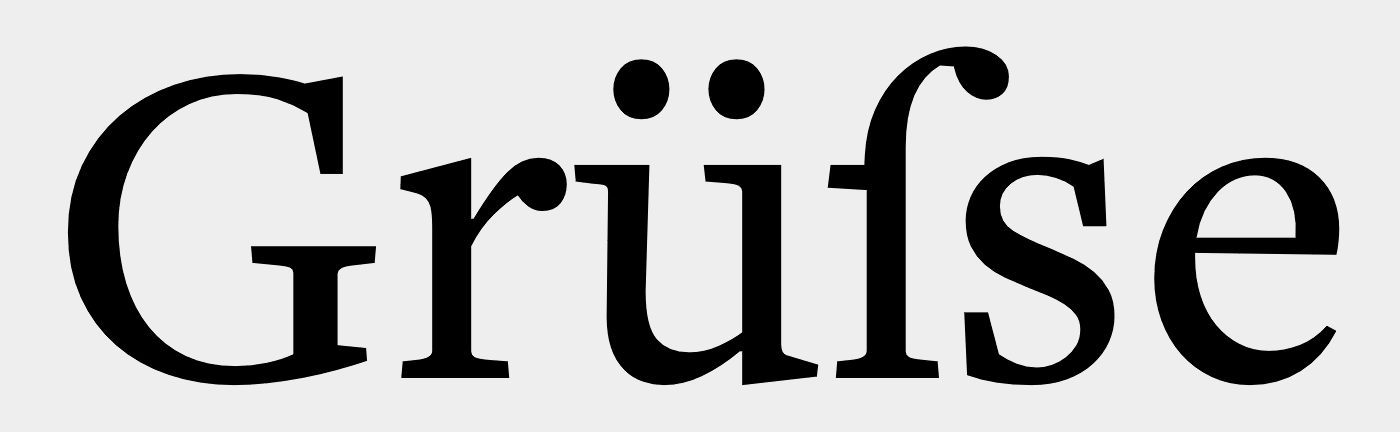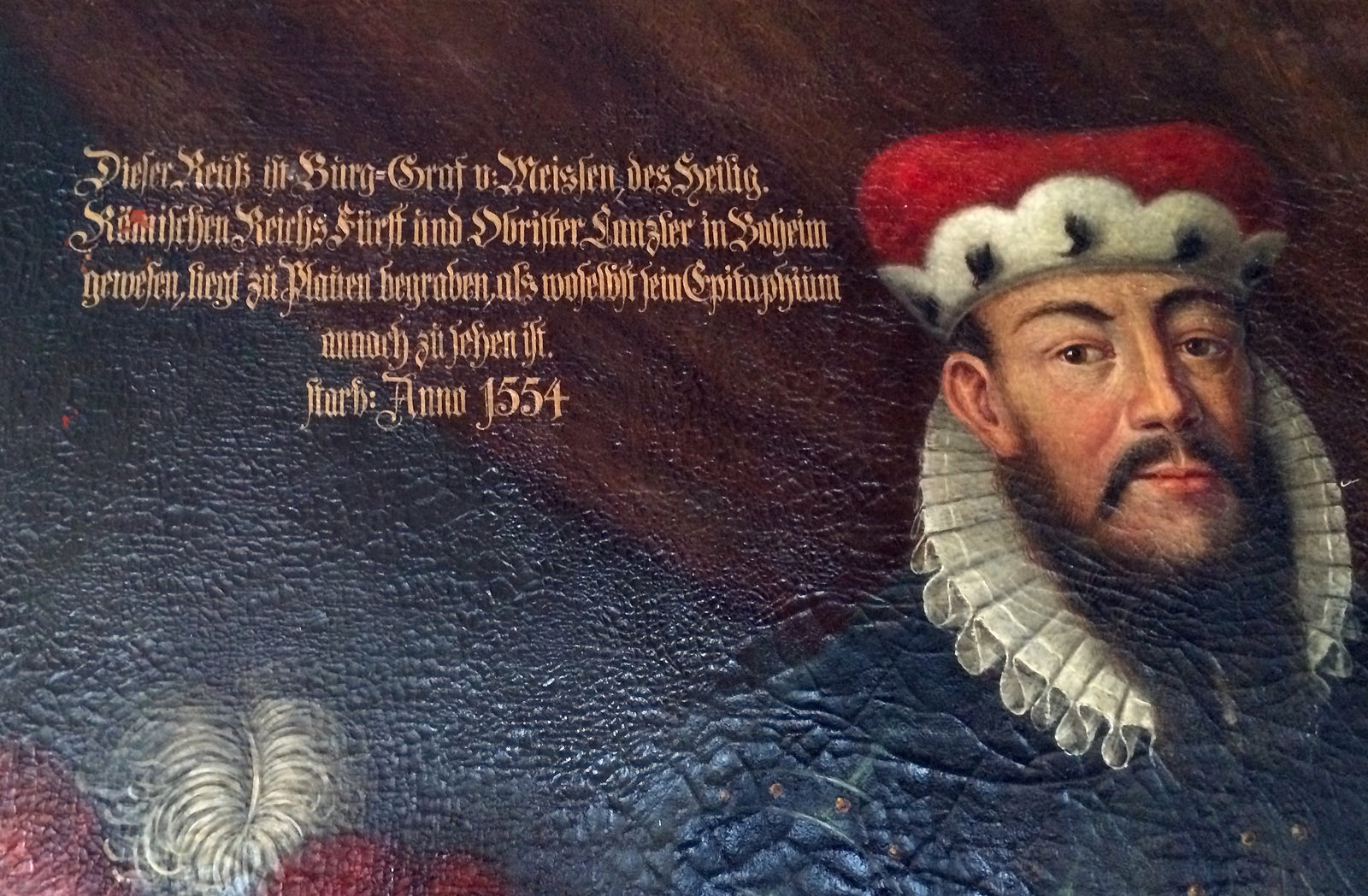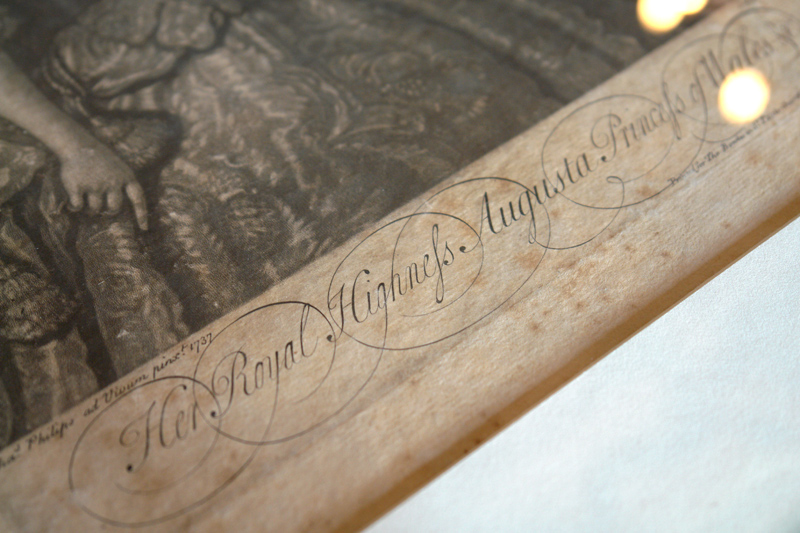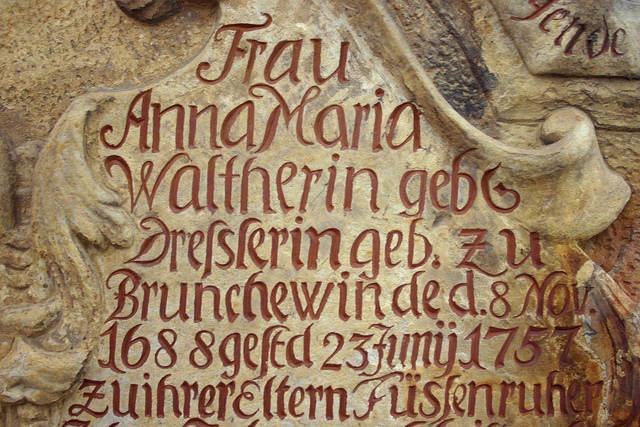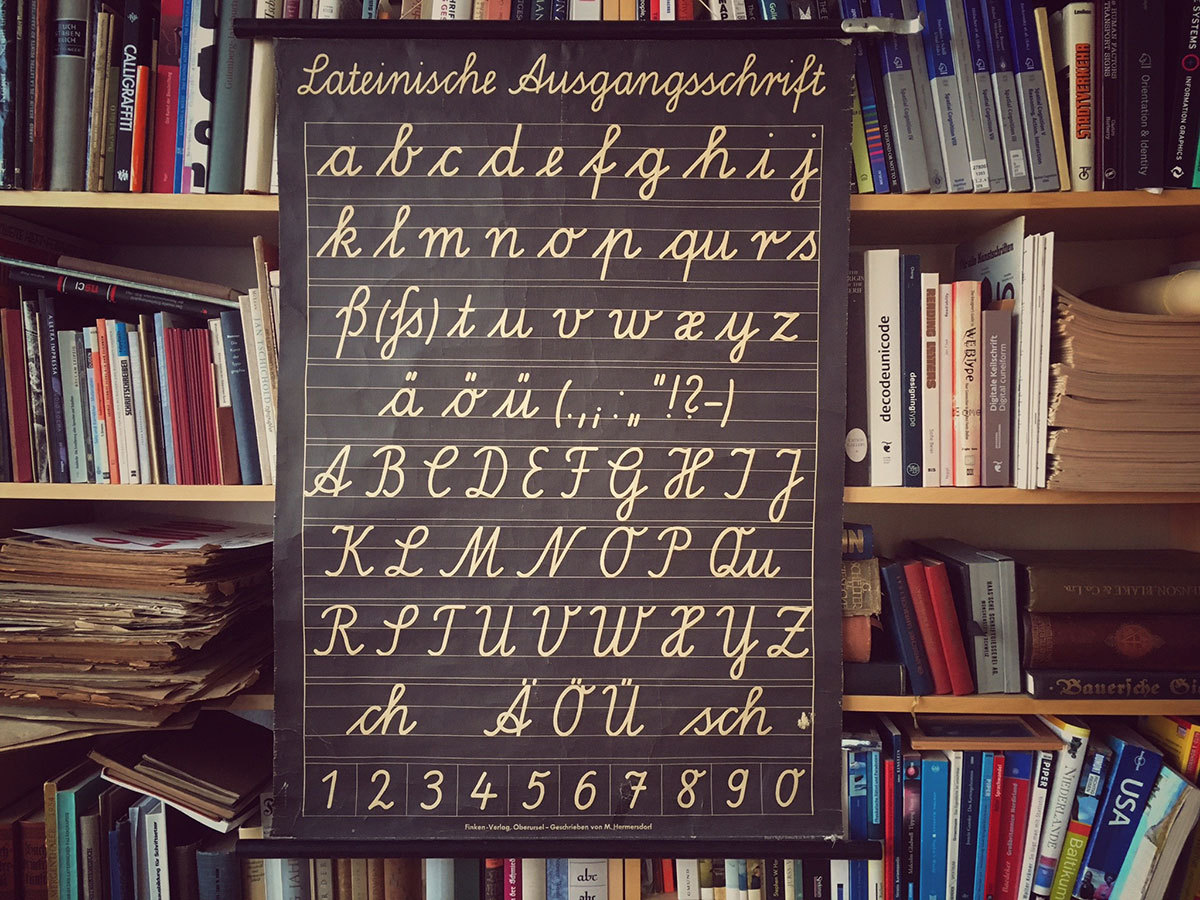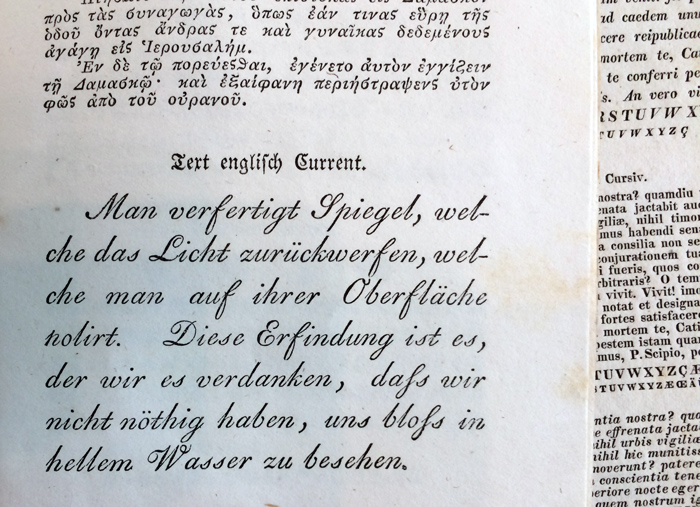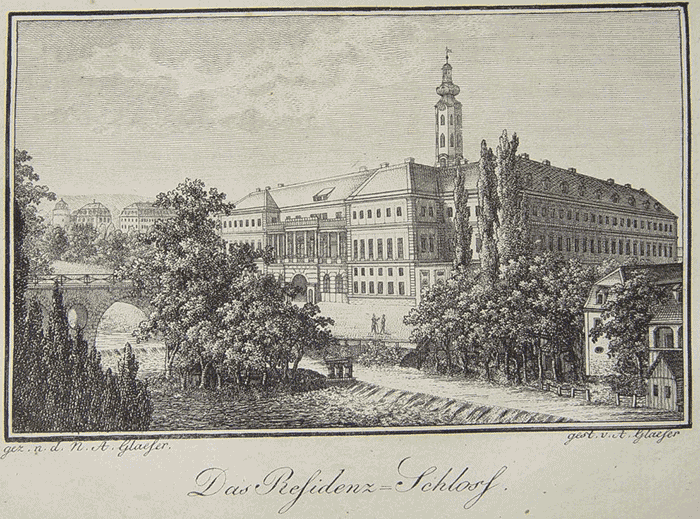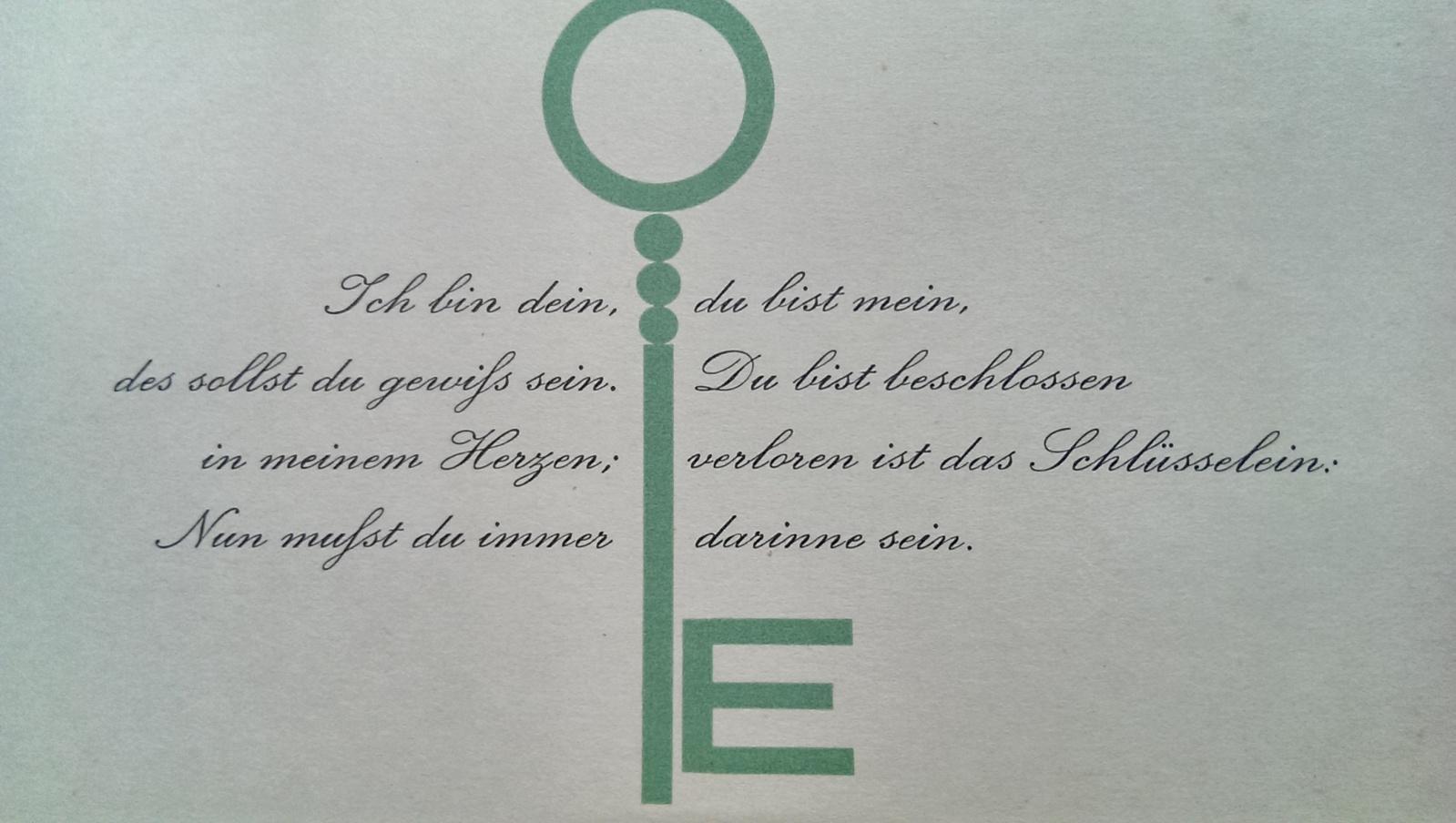
Das ist ein Latein-Schreibschift-langers-s, dieses wurde tatsächlich wie das h in Kurrentschrift geschrieben, und sorgt gerne für Verwirrung bei gemischter Schreibung in alten Dokumenten. Allerdings ist Straſse nicht so wirklich kosher.
Ich habe ja nicht behauptet, das die Glyphe ſ oder als Ligatur als ſs nicht in Ordnung wäre, nur müsste es, nutzt man das lange s (ſ) dann  eben nicht ſs sein, wenn dahinter noch ein e folgt. die ſs-Ligatur ist für die Heysesche s-Schreibung der aktuellen Rechtschreibung gedacht, wenn, wegen der Volalkürzung nicht ß verwendet wird, und man das lange ſ verwenden möchte, z.B. im Fluſsſchiff. in den von Ralf gezeigtem Beispiel steht ſs ja am Wortende.
ich finds auch hübsch, aber auch total verwirrend. will dauernd musss oder Strafse lesen.
Nun, da ich mich in letzter Zeit ziemlich in Kurrentschrift eingeleseh habe, lese ich im ersten Moment hier "muhs" und "Strahse"
Die Schreibschriftvariante ist wirklich hübsch!  :nicken:
In einigen zeitgenössischen Schriften ist diese Glyphe ebenfalls enthalten:
Aber in dieser Satzschrift-Form finde ich sie sehr irritieren, muss ich gestehen. Ich habe hier vor langer Zeit schon mal irgendwo darüber geschrieben, wie sehr mich diese ß-Form beim Lesen stört. Ich habe das komplette Buch »Wirklich gute Logos erklärt« durchgelesen, aber ich habe mich mit zunehmender Seitenzahl immer mehr über diese Buchstabenform der verwendeten serifenlosen Fließtextschrift geärgert, weil ich da immer immer immer »fs« gelesen habe. Das ist in meinen Augen reine Gestaltereitelkeit und kein Dienst am Leser. Sorry!  :-)
Ja, ich denke ebenfalls, dass die Variante für heutige Lesegewohnheiten ungeeignet ist. Ich mutmaße, dass dieses Eszett auch eher zufällig in der Schrift gelandet ist. Denn in der Pro-Version, die später erschienen ist, wurde diese Eszett-Form ersatzlos gestrichen.
Vielleicht war es ein Experiment. Oftmals mag ich ja auch so alte Dinge und finde, dass es da in unterschiedlichsten Bereichen viel Bewahrenswertes gibt. Und wenn ein Schriftgestalter einen funktionierenden Weg findet, in seiner Schrift charmanten Reminiszenzen an Schriftdetails von Früher™ einen Platz zu geben, dann bin ich da sehr zu begeistern. Aber die Betonung liegt auf funktionierend. Wenn das ungewöhnliche Zeichen sich nicht durchsetzt im Sinne einer breiten Akzeptanz der Anwender, dann sollte sich der Gestalter vernünftigerweise von seiner Idee trennen oder sie zumindest in ein kleines Seitenfach der Glyphenschatulle umplatzieren und eine gängigere Buchstabenform an ihre Stelle legen. Das macht das Gestalterherz zwar schwer – aber der Anwender dankt es ganz bestimmt.
(Man stelle sich nur mal einen Moment vor, Paul Renner hätte die Futura nur in der extrem geometrischen Ursprungsform herausgebracht. Dann wüssten wir heute vielleicht gar nicht von ihr …)
Generell ist diese Form nicht nur für heutige Lesegewohnheiten befremdlich, oder sogar hinderlich, sonern eben auch nur wirklich am Wortende oder vor einen Wortfuge nutzbar, aber eben nicht in Grüſse oder Straſse denn daſs würde man dann Straſs-e bzw. Gröſs-e lesen müssen.
In sofern ist das ein schlechter Ersatz als besondere Form des ß und eigentlich dann nur in der (aktuellen) Heyseschen S-Schreibung als Schluſs-ss-Variante einsetzbar.
Auch diese Unterscheidung ...ass = Vokal wird kurz ausgesprochen und ...aß Vokal wird lang gesprochen, was ja einer der Vorteile der reformierten Rechtschreibung ist, ginge hierbei verloren, da dies ja deutlich 2 Buchstaben sind, daſs diese auf einem Kegel sitzen, sieht man ja nicht.
… aber eben nicht in Grüſse oder Straſse denn daſs würde man dann Straſs-e bzw. Gröſs-e lesen müssen.
Nö. Wer sagt das?
Du sprichst von einer theoretisch möglichen Satzkonvention, die es überhaupt nur dann geben könnte, wenn auch gleichzeitig ein ſ im Einsatz wäre und zur Lesekonvention gehört. Das ist in Roberts Text aber klar nicht der Fall. Diese ſs-Ligatur wurde eine Zeitlang einfach als eine grafische Variante des ß eingesetzt. Mit den orthografischen Zusammenhängen, die du da erklärst, hat das alles nichts zu tun.
Noch ein Beispiel:
… und in Druckschrift bedeutet das »Claßen«, nichts sonst.
Rein gefühlt und ästhetisch finde ich es so auch besser – wie bei anderen Dopplungsligaturen™ ist der zweite Teil höher und erzeugt somit eine aufwärtszeigende Diagonale  :-)
Ich kann zu dem Thema beitragen, daß “ſs” schon im 15. Jh. gängige Schreibung für “ſſ” war. Warum in ein und demselben Text manchmal “ſſ” und manchmal “ſs” steht, ist mir allerdings noch immer nicht klar, und falls es jemand hier erklärt hat, habe ich es nicht verstanden. Bitte nochmal für Doofies!
Auf alle Fälle kann es aber durchaus sein, dass die Schreibweise sſ nicht an einer Wortfuge schlicht ein Schreibfehler ist.
Zumindest drängt sich mir bei Meisſen die Aussprache Meis - ſen auf, irgendwie wie soi ein nordischer Name, z.B. Michaelsſen.
Daraus ableiten zu wollen, dass dies eine regelgerechte Variante war, wäre in etwa so, als ob Sprachforscher in ein paar Jahrhunderten die Rechtschreibung um den Jahrtausendwechsel 2000 untersuchen, und aus den häufigen Auftreten von Getrennt Schreibung von Komposita ermitteln, dass dies einer in unserer Zeit zulässige Regel Varante ;-) ist.
Das ist, vielfach im ländlichen, umgangssprachlichen Umfeld auch heute noch anzutreffen. Hab ich selbst noch vor gar nicht so langer Zeit erlebt
Ist auch nicht uncharmant, eigentlich. Obwohl heute wohl der Sinn dafür fehlt. Wenn Du Frau Müller heute mit »(Frau) Müllerin« ansprächest, wäre die Wahrscheinlichkeit hoch, sie nähme es krumm.
Es ist auch weniger, dass es in der direkten Ansprache genutzt wird. ich hatte das sinngemäß so erlebt: „Gehn‘s am besten in den Laden der Müllerin...“ die Müllerin wurde dann aber von jedem „Frau Müller“ angesprochen.